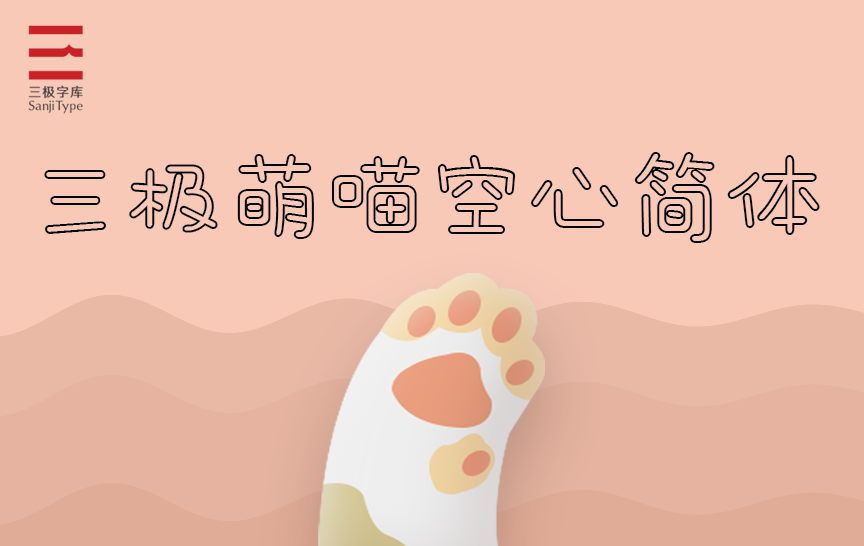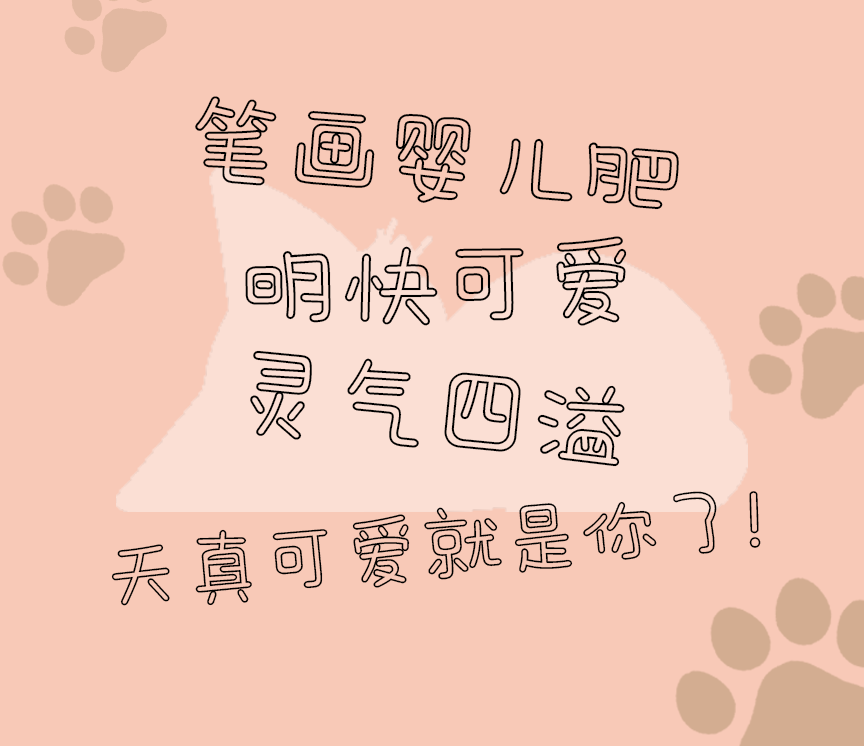
三极萌喵空心简体
字体名称:三极萌喵空心简体
设计师:罗碧霞,庞丽珊
所属分类:混合字体
三极萌喵空心简体运用空心设计,体现出有立体感,有质感,在设计中应用十分广泛,用儿童写字的简拙,笔画轻松、简洁,童趣随性。字形饱满圆润,轮廓略显臃肥,整体个性明快可爱。适用于少儿类读物、书刊、品牌广告、包装设计以及社交网络个性化用字。